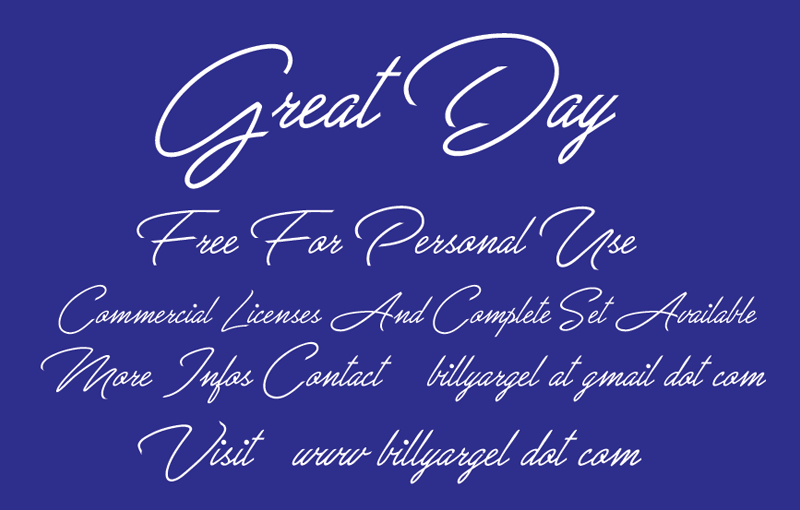
Great Day Font – Download Grátis
A fonte Great Day é uma mão-dura criada pelo designer Billy Argel, disponível gratuitamente para uso pessoal. Esse desenho natural e suave consegue capturar a essência do texto livremente escrita, oferecendo um toque artesanal que pode adicionar um toque especial a qualquer projeto de design. Os detalhes delicados e a variação leve da fonte podem ser usados para dar vida a seu trabalho, seja em cartões de aniversário, cartazes ou até mesmo materiais publicitários. Se você está procurando por uma fonte que realmente destaca o texto sem se tornar dominante demais, Great Day pode ser perfeito para você. Além disso, Billy Argel disponibiliza informações adicionais sobre como obter um license comercial a partir de seu site, ou através do email . Visite agora www.billyargel.com e tenha acesso imediato à fonte Great Day. Esta descrição convida o designer gráfico ao mesmo tempo que fornece informações claras e relevantes sobre como usar a font. O tom informativo faz com que seja fácil de entender, sem adicionar detalhes ou características que não estão na fonte original da descrição.